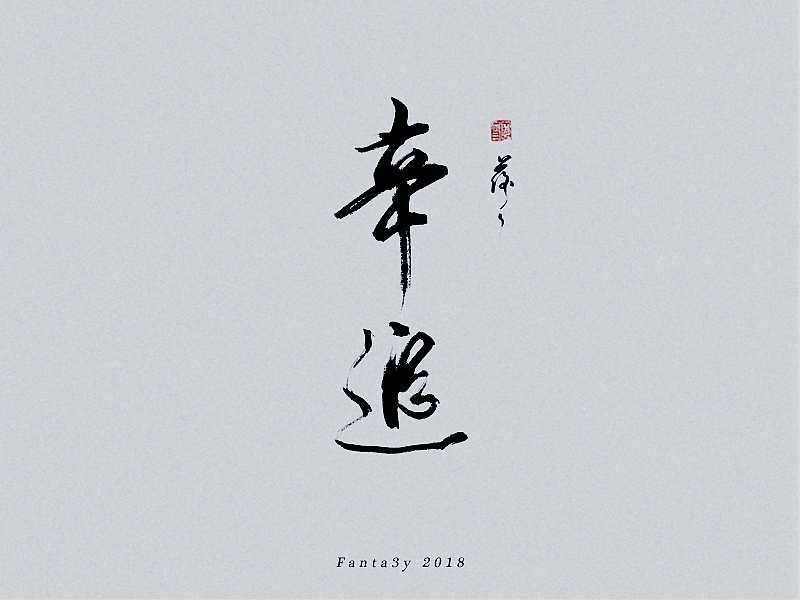
2018年第一弹-近日字迹
最近都在忙着适应新工作的事,写字更多的是在舒缓心里的那种压迫感。但是写完都很享受。
我能够感觉到自己的字形在随着自己的情绪而变化,我也在努力让它往好的方向发展。
在越来越成熟的写字的同时,也希望它更稳一些,能够在结构基础上变得不一样那就最好了。
毕竟写字如作图,也是有灵魂的,也不能一层不变。
万事加油,练习的话会有结果的。
看完复联三写的,其实是内心的情绪走不出来,在这里我就不剧透,反正想打灭霸就对了。
当时看这个电影的时候我就知道,没有感同身受,但能够感同身受的人,她一定也有更多说不出的难言之隐吧。
银魂倾城篇里的一段话。
给朋友店里写的茶类,也很开心她在自己喜欢的世界里做得开开心心的。
好朋友做的食品写的标题,后来她用了一个可爱风格的,给她变成了logo。
啊,落落终于出一套,坑也填满了。可能这个怀旧风要出一个系列 还在整理。
很喜欢这句话,所以在写的时候虔诚而慎重。
自己论坛里的店子的话。
银魂倾城篇,银魂一生推!
给朋友写的标签。目前已上架,自己做的超级棒。